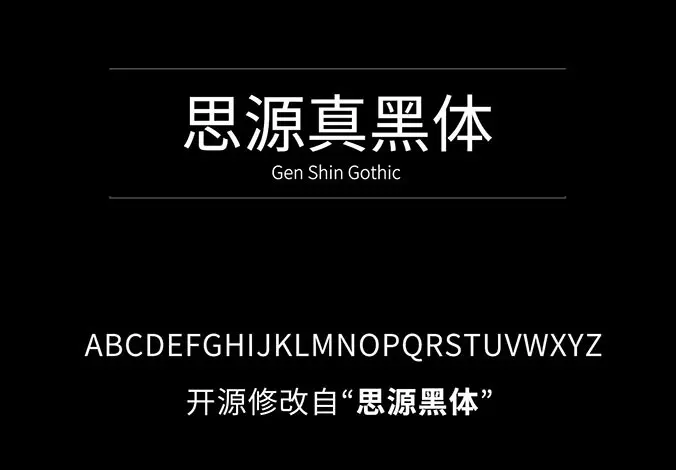
思源真黑體(源真ゴシック)是基於開源字體“思源黑體”修改衍生而來,支持簡體中文、繁體中文以及日文三種語言,保留了思源黑體原版的優雅以及高可讀性的特色,也是提供了 7 種不同的字重、3種字形樣式 (包括等寬字體、比例字體)。格式上轉換成 TrueType (TTF) 版,細節上也做了很多的調整與變化,使得整套字體看起來更加銳利清晰,更適用於大量文字閱讀顯示、代碼編程、排版、打印等。
思源真黑體的字重共有“一般、標準、中黑、細體、特細體、粗體、特黑體”7種。另外還有等寬字體 GenJyuuGothic - Monospace (適合用於編程寫代碼)、Proportional 比例字體 (字符寬度不同)。細節上看起來更加銳利清晰,更適用於大量文字閱讀顯示、代碼編程、排版、打印等。